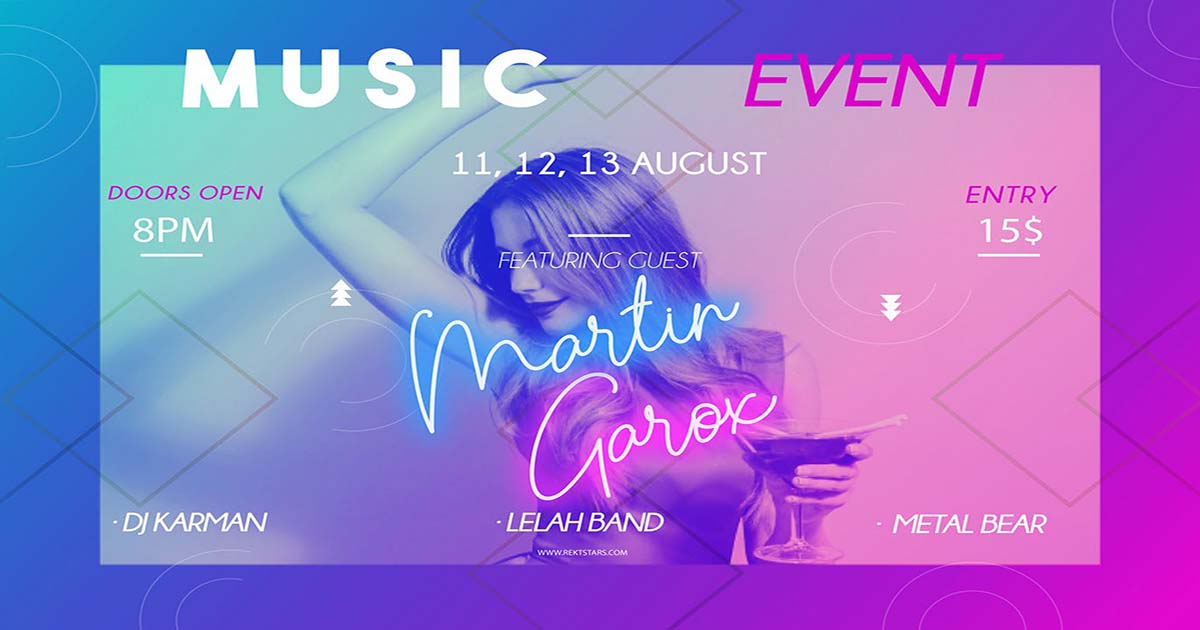
Tải Font Chữ Đẹp Neon Miễn Phí Để Design 2021
Neon là một trong những xu hướng chưa bao giờ hết hot, font chữ neon mang lại một cảm giác hoài cổ. nhưng vẫn bắt mắt và rất hiện đại. Hơn thế font chữ neon còn được nhiều nhà thiết kế vận dụng để tạo ra cảm giác từ tương lai. Nếu bạn cần font chữ miễn phí về noen thì đây là bài viết dành cho bạn.